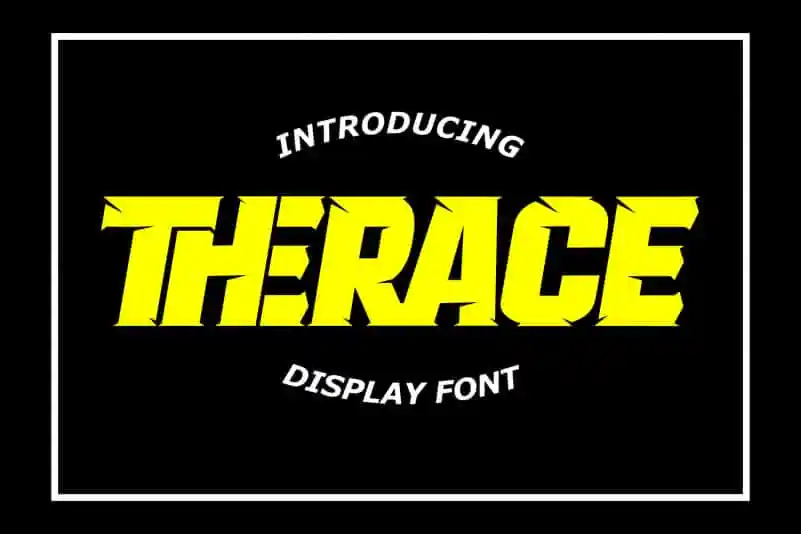
Therace Display Font – Download Grátis
A font Therace Display é uma escolha perfeita para quem busca uma aparência elegante e sofisticada que se sobressai entre os demais. Esta font foi criada pensando na importância de destaque em um design, seja ele num logotipo audacioso ou no rótulo de uma embalagem luxuosa. Com linhas afiadas e textura robusta, Therace Display oferece um estilo poderoso que convida os designers a explorar suas capacidades em diversos ambientes gráficos. Seja para criar um logo impactante ou adaptá-la no design de embalagens sofisticadas, essa font é uma ferramenta valiosa para qualquer designer profissional buscando uma solução única e impecável. E com sua elegância intrínseca e poder visual, Therace Display definitivamente merece ser uma parte integrante da sua arsenal gráfica.